甲骨文是我国最古老的一种字体,它起源于1300年前,是商周时期王室用来占卜记事一种文字,同时也是我国最早期的汉字,因当时并没有纸张印刷技术,所以甲骨文大多数都是刻印在龟甲或兽骨上面,因此才被称为“甲骨文”。
四川考生黄蛉以一篇甲骨文作文成为了那一届的高考焦点,这消息一出,引来无数高校的关注,而他的高考总分才428,这个分数,上个好一点的二本都够呛,但是黄蛉却被不少一本高校争抢着破格录取,这一切都是因为他那篇别具一格的甲骨文作文,因为当时我国甲骨文还才翻译出1000字,所以他不仅写了甲骨文,还运用了青铜铭文,大篆等古文字题,且书写的非常标准。
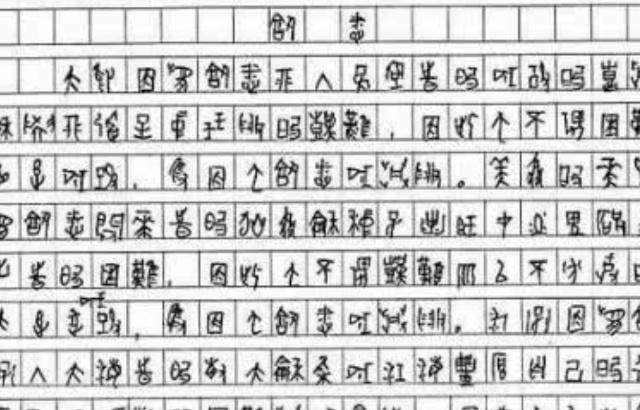
国内某网站上出现了一篇帖子,名为《高考阅卷花絮:四川惊现甲骨文作文》,发帖者是一位现场阅卷老师,当年作文题目是《熟悉》,刚好他就改到了黄蛉的试卷,经过粗略察看,他发现上面既有甲骨文,还有篆体、青铜铭文等,突然他就“蒙了”。
于是立马向组长汇报,组长向语文质检组报告,质检组又找来了专家,专家们饶有兴趣地翻译了黄蛉的作文,书写工整且字体标准,但就作文内容而言,严重离题,所以最后只打了6分。
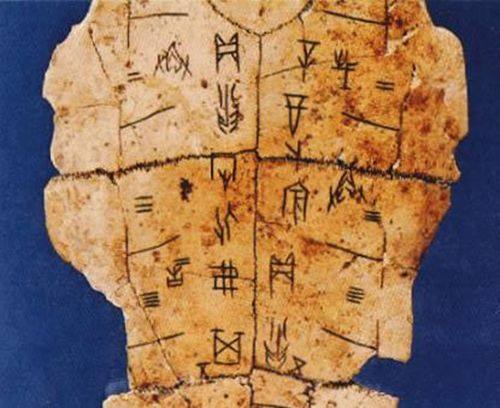
事实上,这并不是黄蛉第一次高考了,早在2008年时,他就参加过一次高考,但是因为成绩不理想,最终选择了留校复读,而这一次,黄蛉在高考前,突然想到复旦大学刘钊破例录取三轮车夫的事,也选择了冒一次险,他怕自己的作为不出彩,刻意花了一把半小时,运用了多种不同的古文字体才写完。
结果和他预想的一样,因为这篇没几个人认识的古文作文,让他成为了网红,并成功吸引到了复旦大学刘钊教授的注意,6月25日,黄蛉受邀前往上海拜访刘钊教授,虽然他一直对黄蛉赞不绝口,但却表示,黄蛉看的书太少,基础知识不够,暂时还达不到复旦大学破格录取的标准,希望他在大学时好好深造,考研的时候可以考虑考虑。